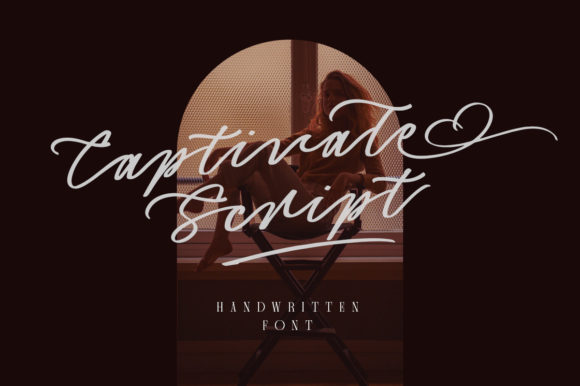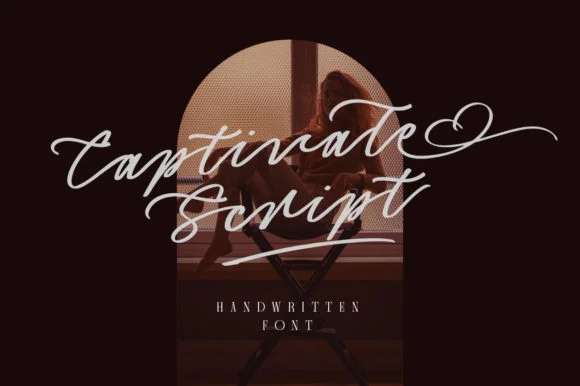
Название: Captivate Script Font (2021)
Captivate Script - это нежный, легкий и красивый шрифт.
Он добавит роскошную искру в любой дизайнерский проект, который вы захотите создать!
Влюбитесь в его невероятно универсальный стиль и используйте его для создания эффектных дизайнов!